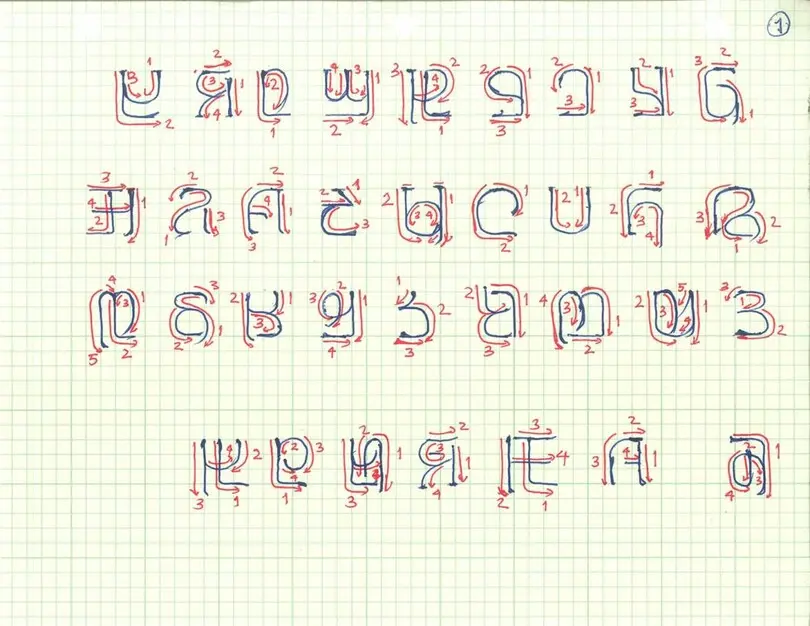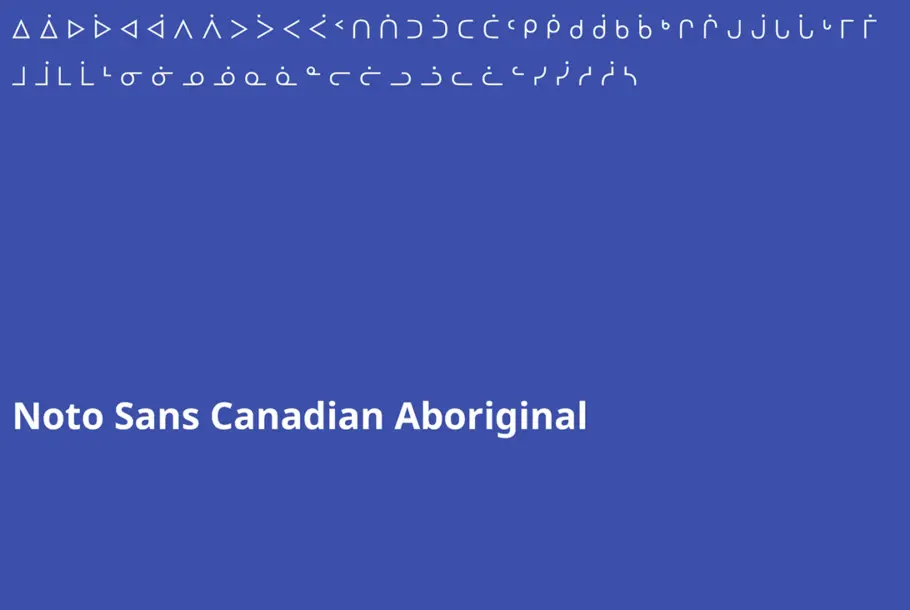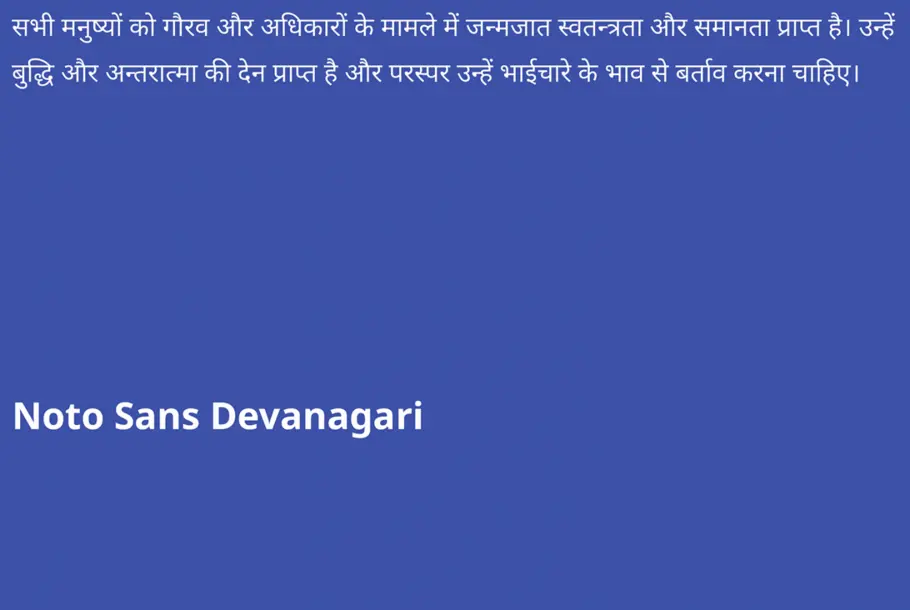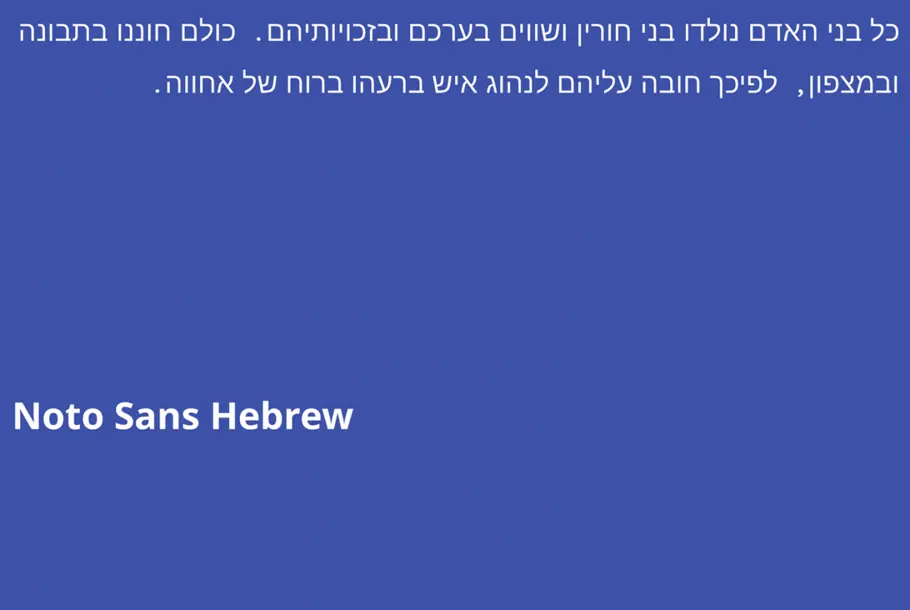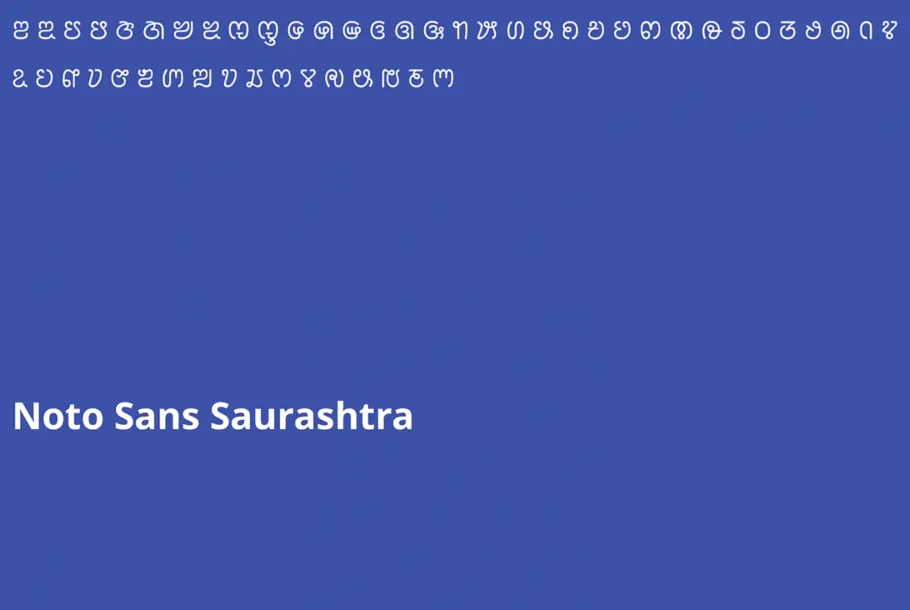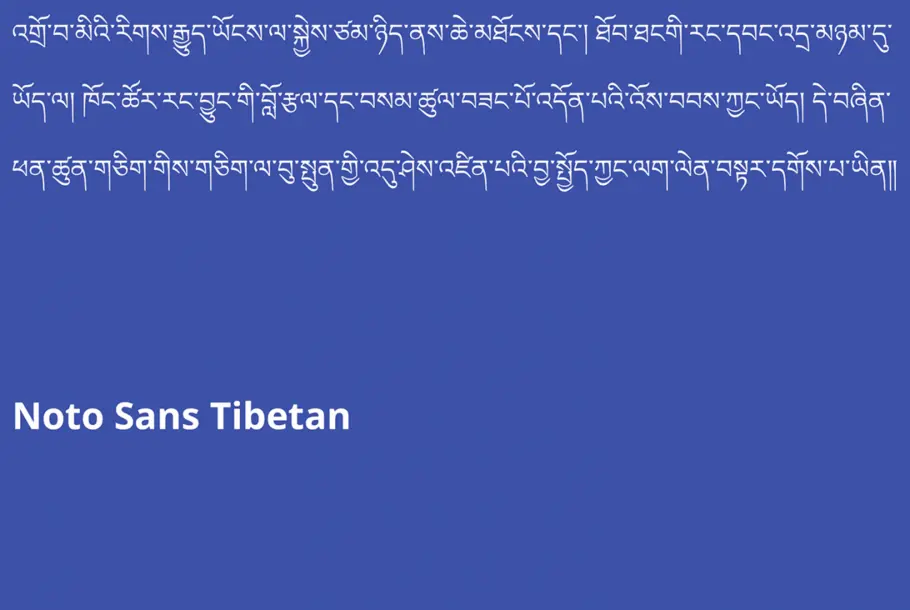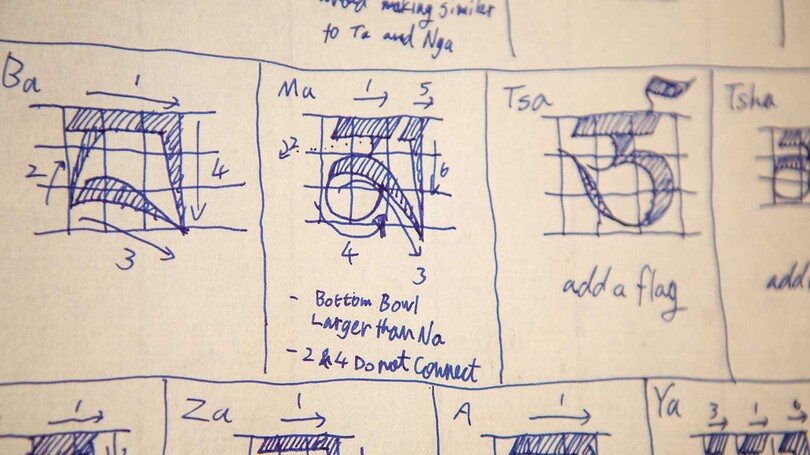
800を超える世界の言語に対応するNoto for Google書体の開発
制作に5年を要した書体、Google Notoは、100を超える筆記体系、800の言語、および数十万の文字に対応しています。Google社とMonotypeが共同で制作に取り組んだNotoフォントは、世界中の何十億もの人々がデジタルコンテンツにアクセスできる本当の意味での普遍的な世界共通のコミュニケーションツールです。
依頼:「豆腐文字をなくす」
GoogleのMonotypeへの依頼は、次のように単純明快で簡潔なものでした。「豆腐文字をなくす」 – 豆腐とは、コンピュータやサイトで特定の文字のフォントがサポートされていない場合に表示される空白の四角形のニックネームです。このGoogleからの要望を満たすために、Monotypeでは、ユニコードコンソーシアム規格に含まれている800以上の言語に対応できる単一の書体ファミリーを開発しなければなりませんでした。
No More Tofu
Tofu is an old nickname for the boxes that appear when a computer lacks support for a particular writing system or character.
この途方もない開発作業では、初めてデジタル化される複数の珍しい筆記体系をはじめ、前例がないほど膨大なスクリプトとの調和のとれたデザインが必要でした。GoogleインターナショナリゼーションエキスパートのBob Jung氏は次のように述べています。「これは本当に驚異的なプロジェクトでした。振り返ってみると、自分たちが取り組んだプロジェクトがいかに野心的であったかということに自分自身でも驚きを覚えます。」
「Notoの目標は、デバイス用のフォントを開発することでしたが、情報の保存にも非常に高い意識がありました。」と、付け加えました。「あまり使用されない言語、純粋に学術的な言語や使用されなくなった言語でも、その保存は非常に重要だと考えています。」
このプロジェクトでは、オープンソースデザインの理念に基づき、世界中のデザイナーや言語の専門家と連絡を取り、それぞれの文字の形を完成させました。この書体が、現在の段階に到達するまでには、5年を超える月日を要しました。Notoでは、各分野の専門家と協力してさまざまなスタイルのニュアンスを調査し、そのスクリプトを使用しているコミュニティの意見をも直接取り入れるという、文化背景や伝統にも考慮した、調和の取れた研究開発が必要でした。
「 石にしか刻まれていない文字もあります。そういった文字をウェブでも利用できるようにしないと、時間の経過とともに石は砂に変わります。そうなると、その描画や筆跡を復元することは二度とできません。 」
研究:文化的な希少スクリプトの保存
新たに特定されたアフリカのフラニ語の筆記体系であるアドラム文字を提供するため、Monotypeはスクリプトの制作者と協力しました。この筆記体系の発明者に直接コンタクトを取ることで、デザイナーは、クリエイターの本来の意図を反映したスタイルの選択肢や機能を組み込むことができ、フラニ語圏のコミュニティでは、初めてデジタルでスクリプトを使用できるようになりました。
Adlam
Monotypeにおける100年以上の歴史の中で初めて扱うアドラム文字では、書体デザイナーとスクリプトの発明者が直接タッグを組みました。これは、アドラム文字での初期段階のスケッチです。
Noto Armenianでは、伝統的な要素と現代的な要素が融合されています。Noto Armenianの作成には、アルメニア人のコミュニティが直接デザインプロセスに携わりました。また、チベット人の修道僧は、Noto Tibetanに専門的な意見を提供してくれました。この縦方向に重ねられるスクリプトにより、Monotypeのデザイナー、大曲都市には特別な課題がもたらされました。大曲は仏教学者の野村正次郎氏が支持する筆記体系だけでなく、修道僧独自の写本も独自に研究し、開発にあたりました。
Tibetan
これは、チベットの書道の伝統を研究しているときに、大曲都市が保管していたノートの1ページです。
また、NotoではUrdu Nastaliqのデジタル版をリリースすることで、Urdu Nastaliqを使用する1億人の人々が利用できるようにしました。さらに、主に遺跡や写本で発見されていて紀元4世紀にまで歴史を遡るアルファベット、オガム文字も復活させました。Monotypeのデザイナー、Steve Mattesonは、Noto Oghamを作成するために、発掘された中世のスクリプトの大量の画像を収集しました。「石にしか刻まれていない文字もあります。そういった文字をウェブで利用できるようにしないと、時間の経過とともに石は砂に変わります。そうなると、その描画や筆記を二度と復元することはできません。」と、Notoのプロダクトマネージャー、Xiangye Xiaoは述べています。
結果:すべての人のためのデジタル言語
Notoは、見出された文化的、歴史的なスクリプトの保存だけではなく、現代のAndroidデバイス、Chromeデバイスに表示されるテキストもサポートし、最大8つのウェイトを備えた膨大な数のスタイルを網羅するデジタル世界の中枢を担うフォントです。また、記号、絵文字、楽譜記号もサポートされています。
そして、この話はここで終わりではありません。文化を越えたコミュニケーションを促進するための幅広い取り組みの一環として、そして、最終的に全言語をサポートするフォントを開発するという崇高な目的のもと、Notoはユニコードコンソーシアムに即して引き続き更新されていきます。